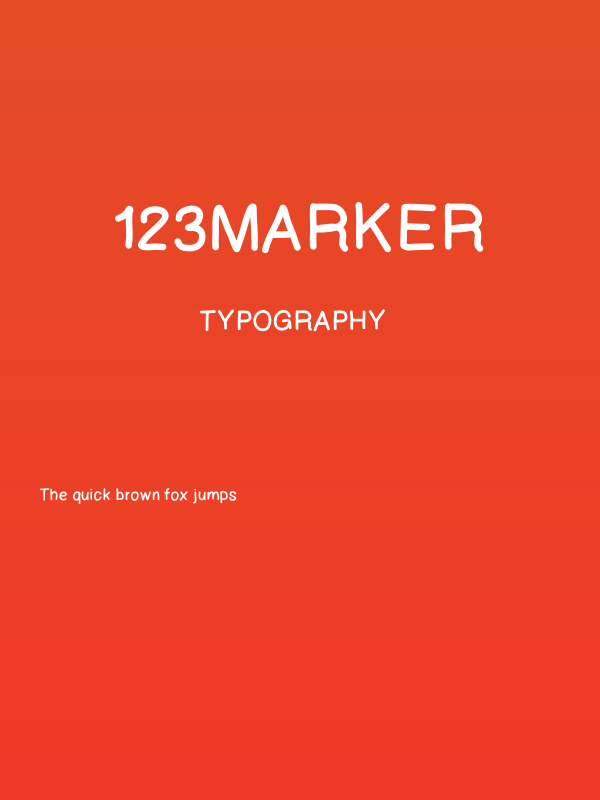
123Marker Font
| Gesamtstil | Casual |
| Anwendungsfall | Headlines, Logos, Informal Text |
| Vorgeschlagene Projekte | Ideal for children's books, casual branding, playful posters, and social media graphics. |